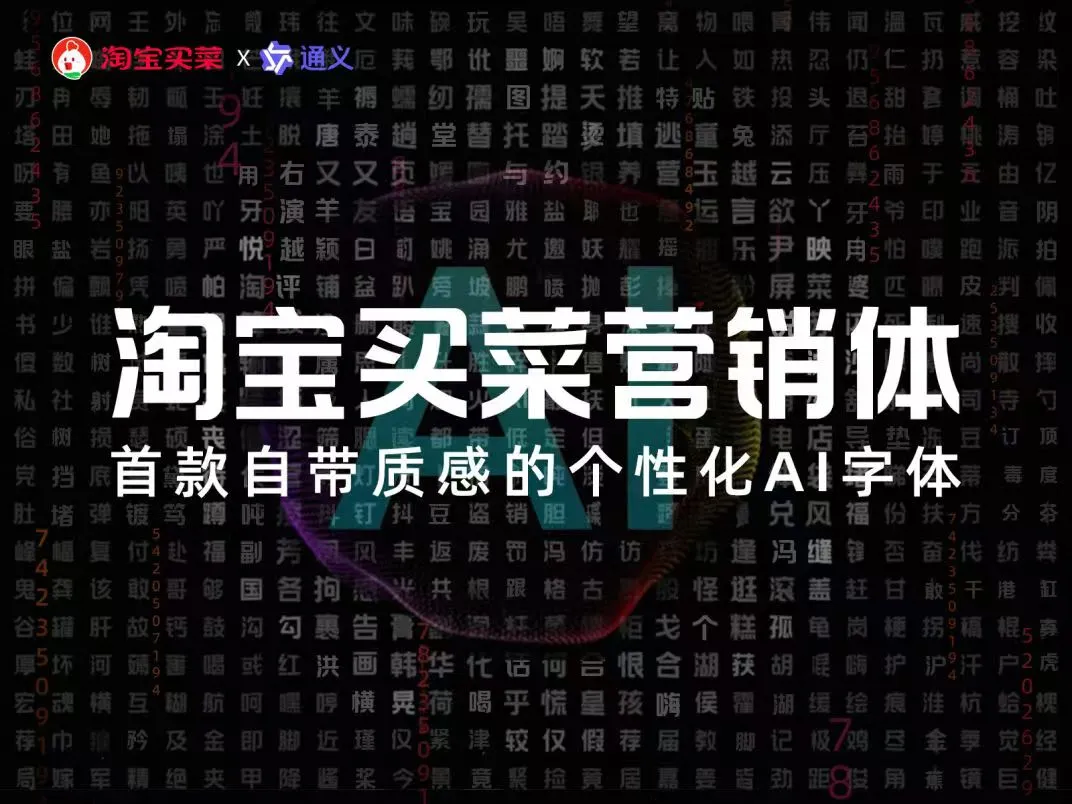
淘宝买菜体(TaoBaoMaiCaiTi)是由阿里巴巴旗下“淘宝买菜”联合通义实验室(通义锦书)共同打造的一款免费可商用的 AI 个性化中文字体,又名淘宝买菜营销体。
淘宝买菜体字正方圆、笔画醒目、粗细均匀,清晰易读,不仅覆盖 GB2312 标准,包含 6974 个汉字。而且通过智能AI技术赋予字体 7 种不同的质感(膨胀质感、炭笔质感、草地质感、水晶质感、金属质感、渐变质感、木质感)。不同的质感搭配不同的设计需求和应用场景,可以发挥这款字体的最大优势。有需要的可以通过字体来源挨个下载体验一下。